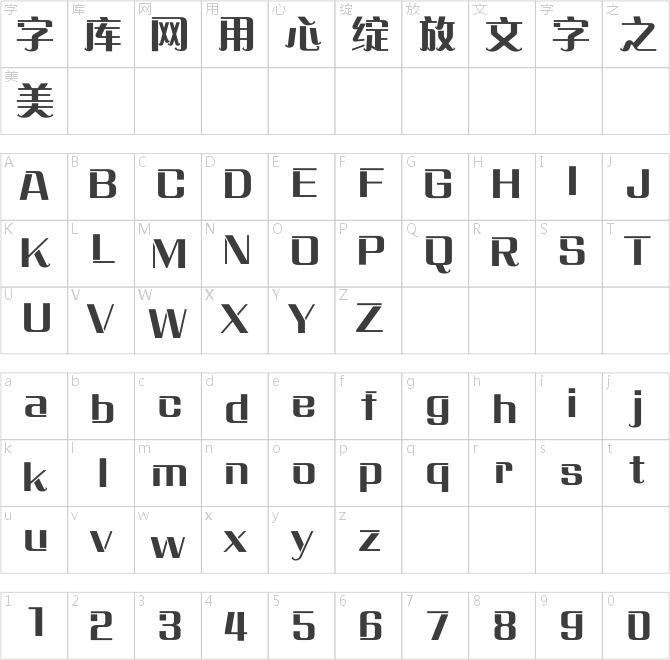
方正贊美體 簡(jiǎn) Heavy 詳情頁(yè)
字體名稱: 方正贊美體 簡(jiǎn)
方正贊美體 簡(jiǎn) Heavy
方正贊美體 簡(jiǎn) Heavy字體字庫(kù)是一款讓人賞心悅目、百看不厭的中文字體,適合各類廣告和產(chǎn)品包裝設(shè)計(jì)應(yīng)用,字體大小3MB,格式為ttf字體,上傳用戶是一直在守護(hù),作者/版權(quán)方為方正字庫(kù)